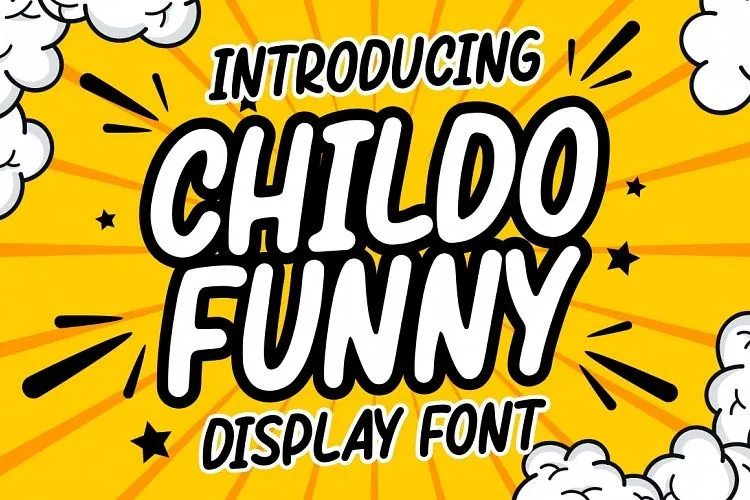
Esse é o Childo Funny Display Font, uma nova opção para designers que buscam dar um toque divertido às suas criações. Introduzida pela Garisman Studio, esta fonte de exibição leva a sensação descontraída e lúdica para os designers brasileiros. O Childo Funny Display é uma tipografia com traços grossos e coloridos que não só inspirou-se em marcadores fortes e brilhantes como também traz um toque alegre e de felicidade para todos nós. Este tipo de fonte exibição é perfeitamente adaptada para qualquer formato de design, seja para textos, impressões, marcas de logotipos, sinalizações ou projetos digitais. Suas características otimizadas oferecem a liberdade necessária para criar designs modernos e criativos em qualquer layout, proporcionando um toque divertido sem sair do estilo bold and fun que já é seu ponto forte. Com o Childo Funny Display Font, você pode transformar seus projetos com uma leveza irônica e uma pitada de diversão, deixando sua marca mais atraente e engraçada no mundo da design gráfico.